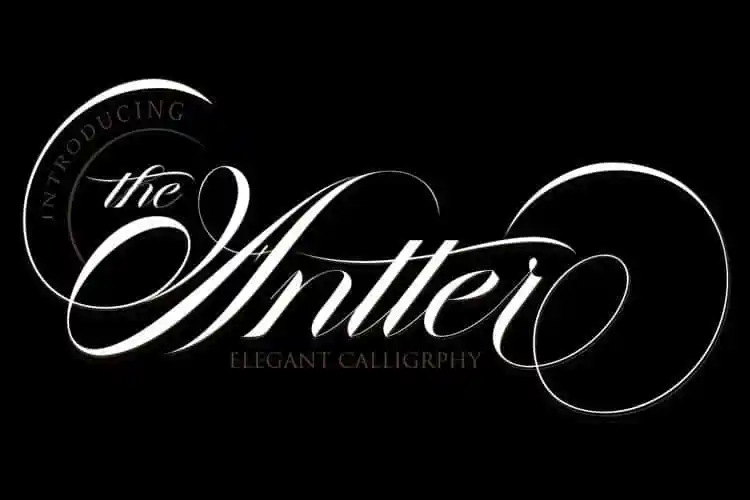
The Antter Calligraphy Font – Download Grátis
A Antter Calligraphy Font é uma tipografia inspirada na calligrafia clássica, projetada para encantar com sua elegância sofisticada e beleza singular. Inspirada nos caracteres decorativos de cartas ou convites antigos, esta fonte apresenta um belo mutirão de letras que se integram a uma tipografia modernizada, oferecendo um toque refinado ao texto clássico. É designada com grande atenção aos detalhes para proporcionar um estilo elegante e sofisticado. Anter é uma opção atraente para fontes, conhecida por seu fluxo suave, pureza feminina e sensibilidade. Incluímos também alternativas de valor decente para muitas letras complexas. Esta fonte atende perfeitamente às necessidades dos formais projetos, como convites de festa, rótulos de embalagem, menus de restaurantes, logotipos, moda, estaçãoaria, novelas, revistas e livros. É também uma escolha agradável para anúncios, selos de produtos ou qualquer outro tipo de uso gráfico que valorize um toque elegante e sofisticado. Essa fonte é perfeitamente adaptada às necessidades formais do design visual, tornando-a perfeita para quem busca uma combinação única e sofisticada entre a estética moderna e o charme dos tempos antigos.